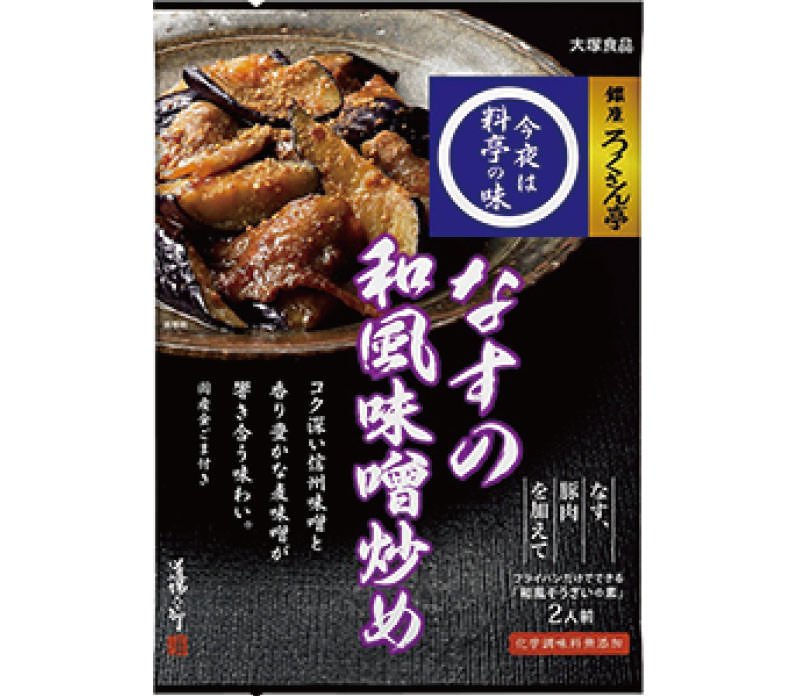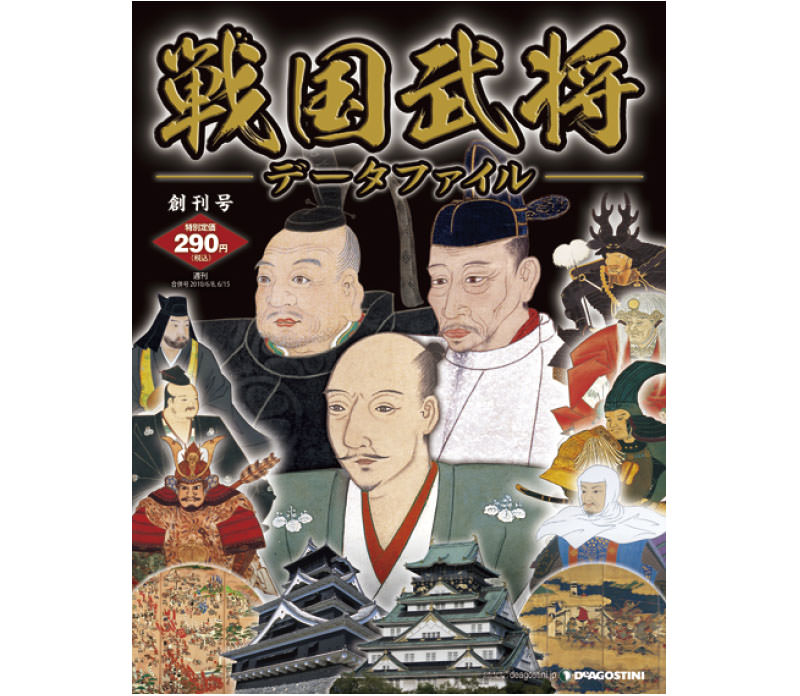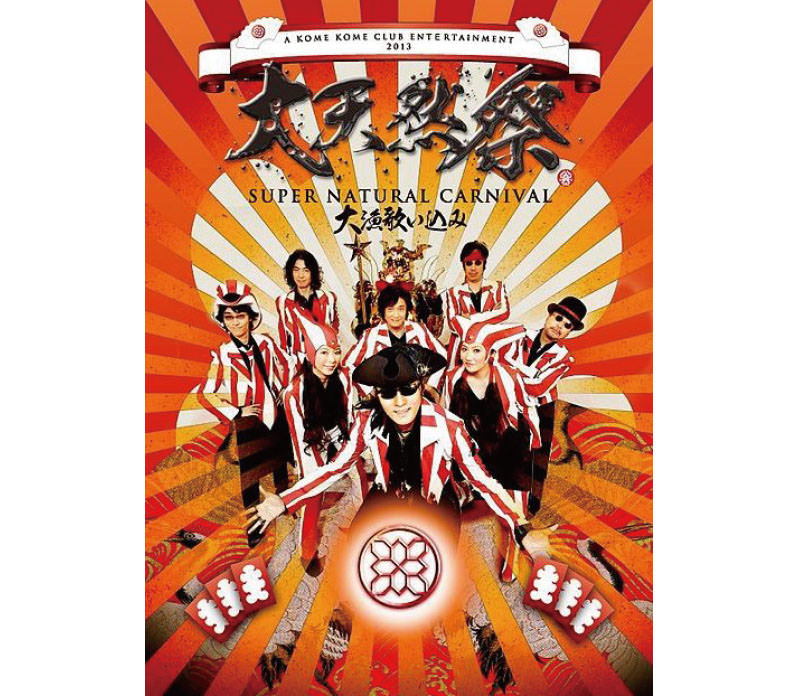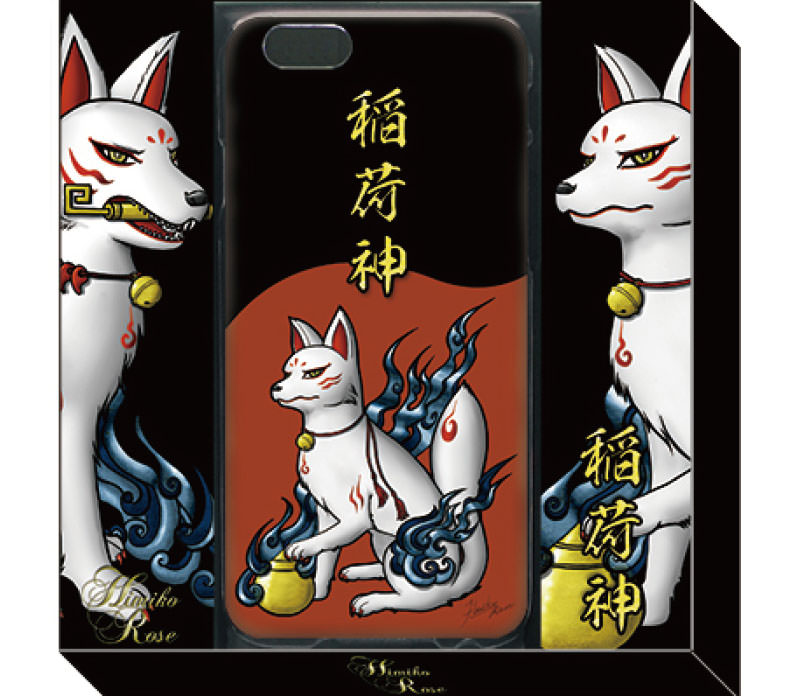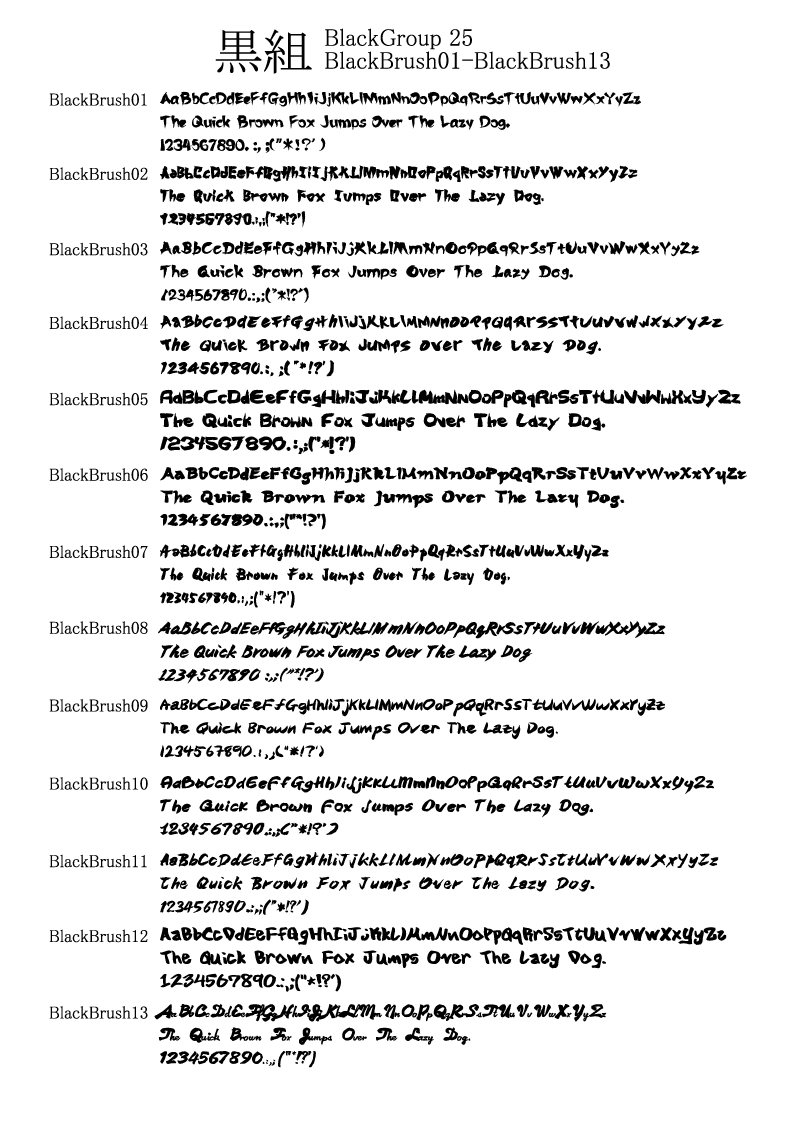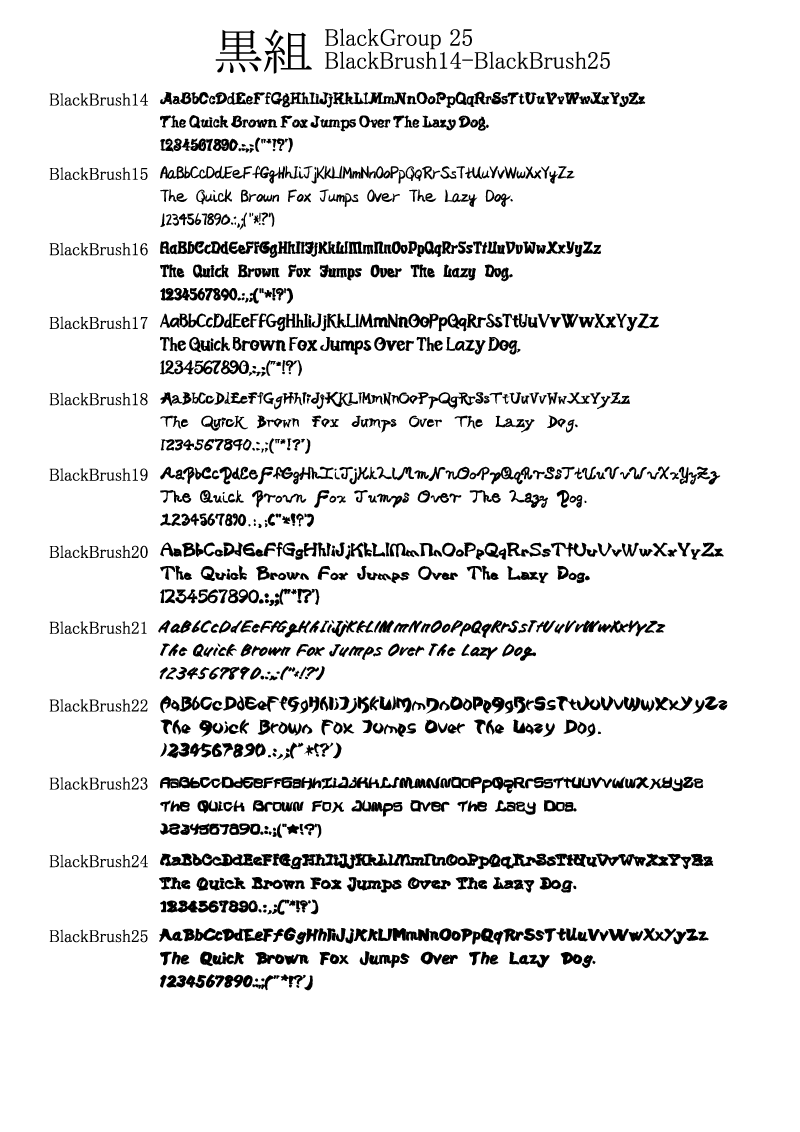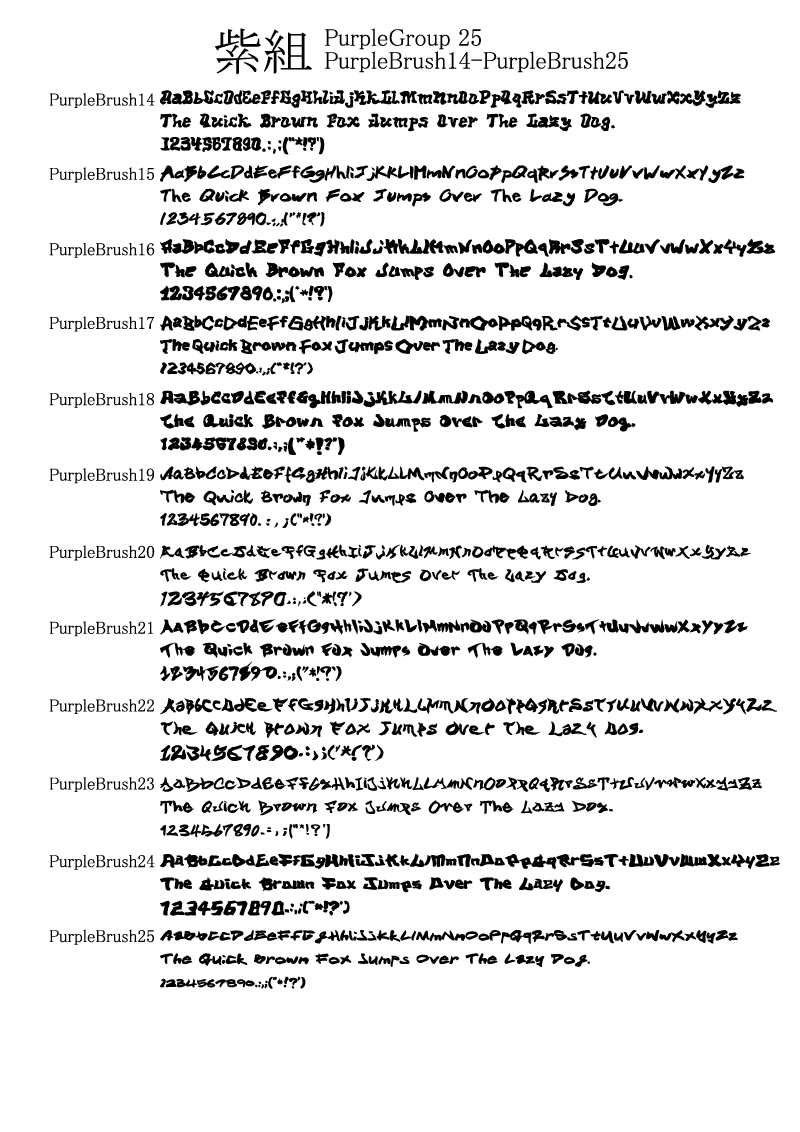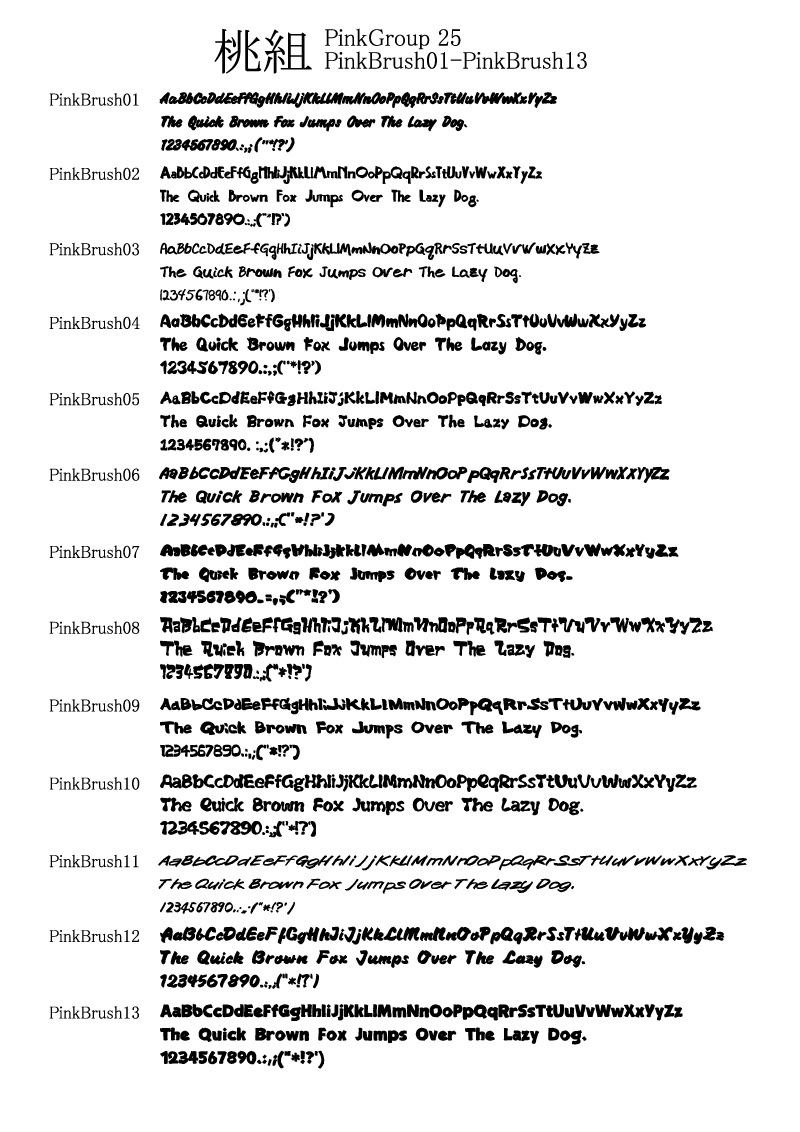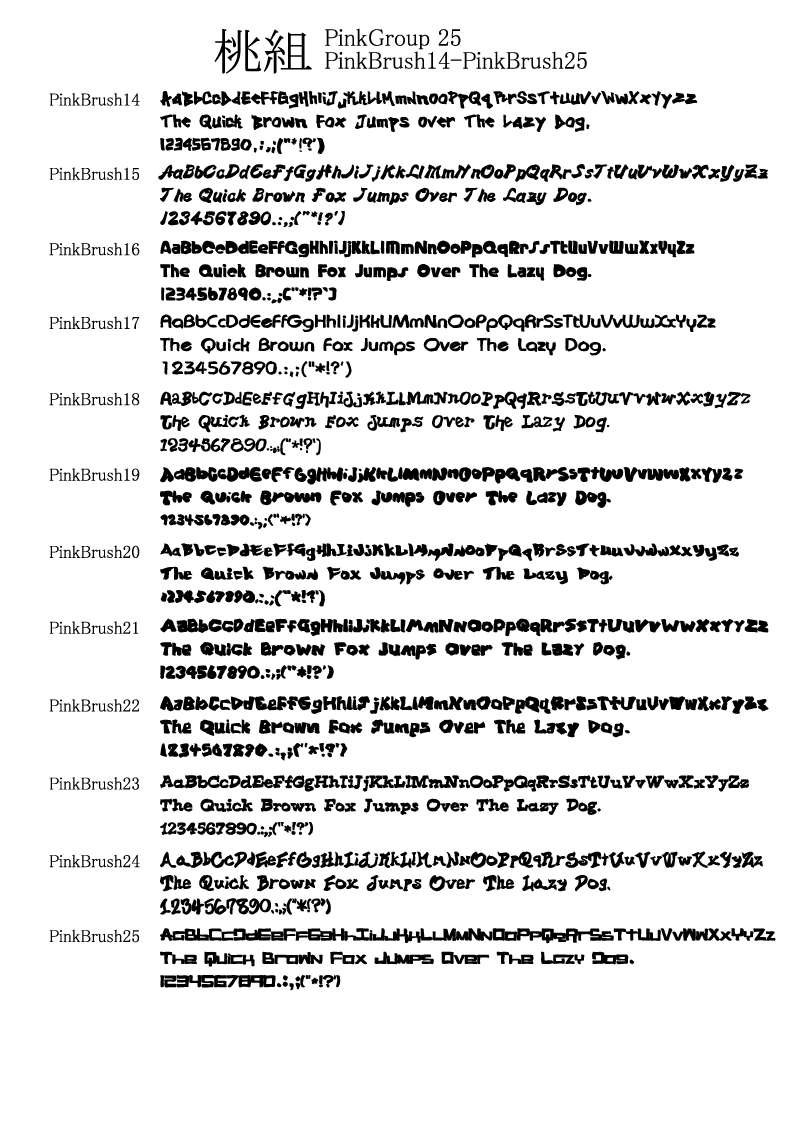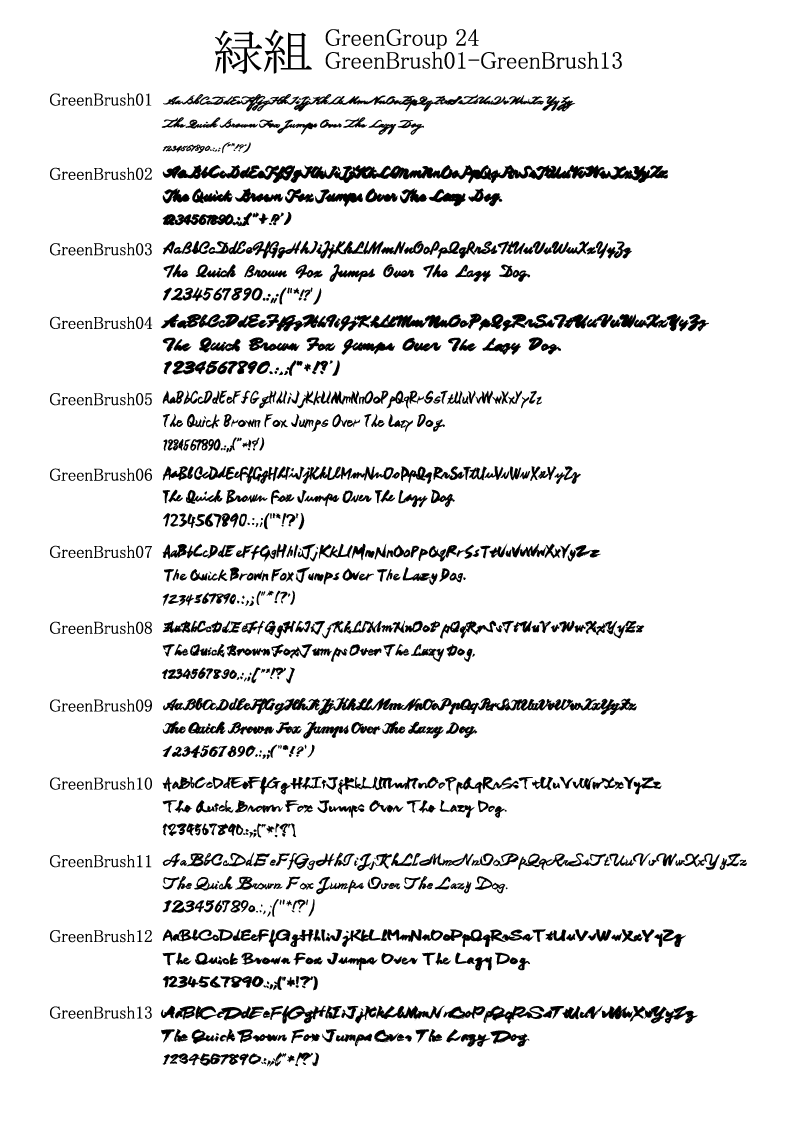
株式会社昭和書体により書家「綱紀栄泉(つなのりえいせん)」の書き綴った毛筆諸本をデジタル化した毛筆書体です。
その特徴は毛筆書体独特のかすれやにじみをより忠実に再現したもので、直筆と見分けがつかないほどの本格的な毛筆書体です。
主に力強いタイトルやキャッチコピーなどの利用に最適で、有名商品のタイトルなどへも多く利用されています。その他、POP、ちらし、DM、飲食店メニュー、和風を表現する媒体やコンテンツなどにも幅広くご利用いただけます。
一般書体よりも約5から50倍のデータポイント数で表現されるかすれやにじみ具合を実現した毛筆書体です。